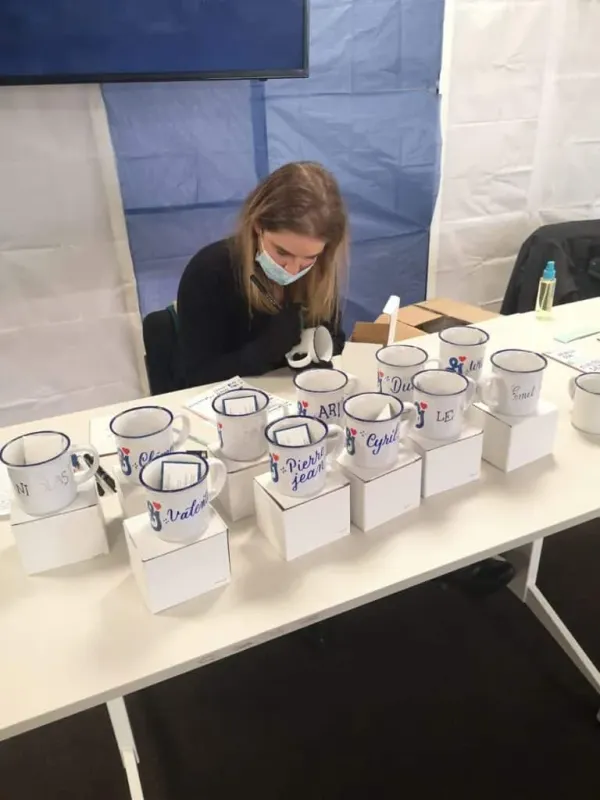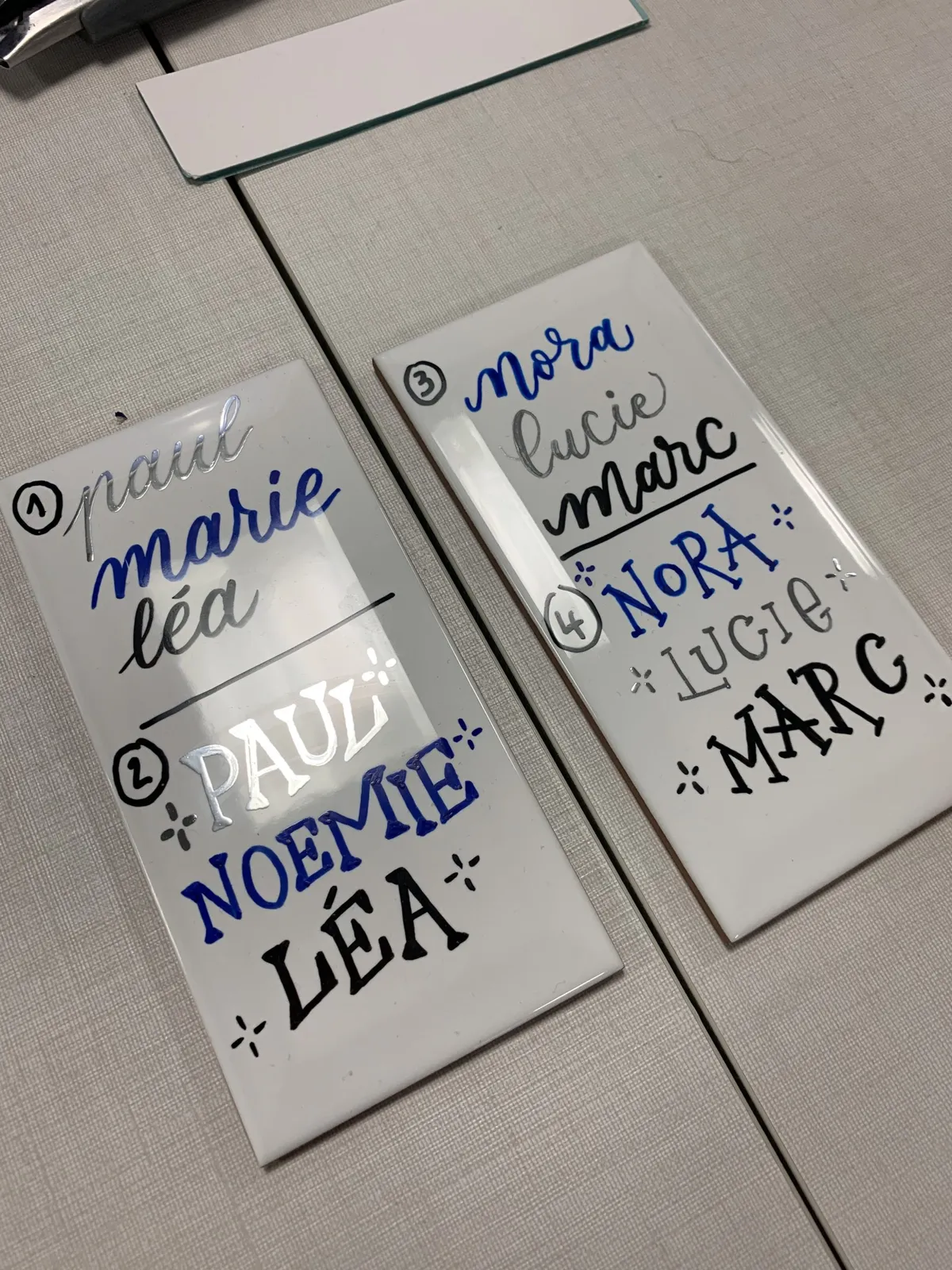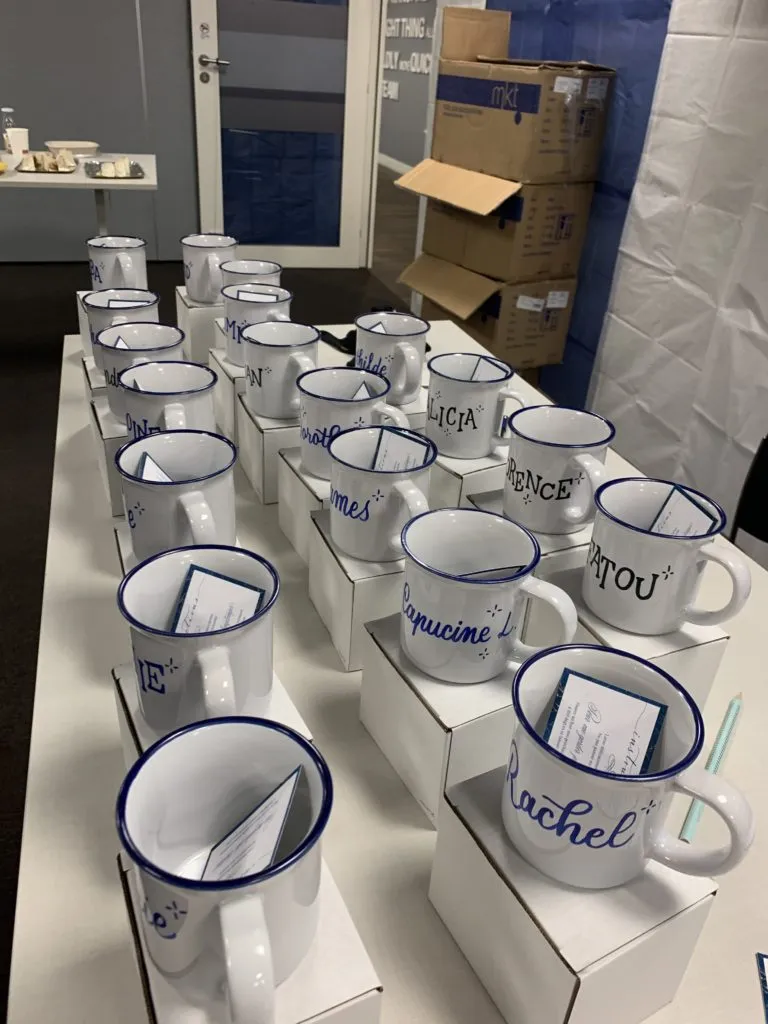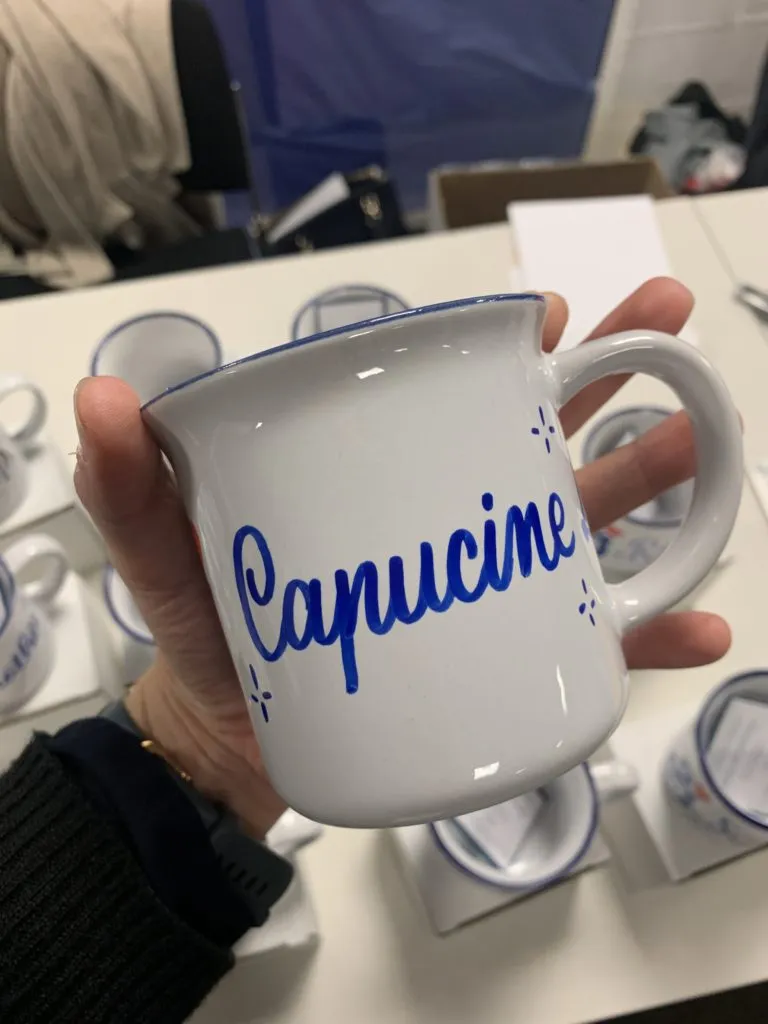
Noël General Mills
Evènement personnalisation
Personnalisation de 120 mugs aux feutres acryliques lors du Noël de l’entreprise General Mills
Proposition de plusieurs types de lettrages et couleurs pour une calligraphie en live devant les employés.